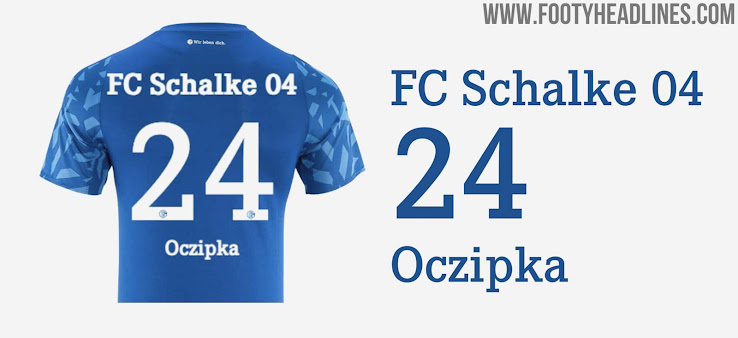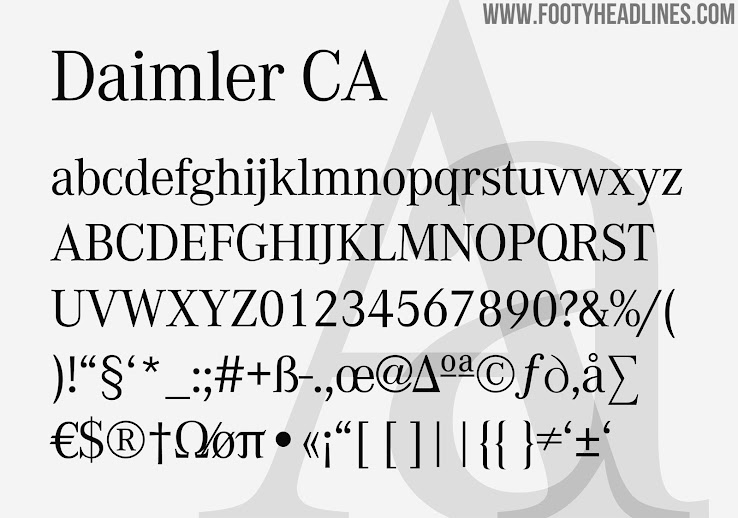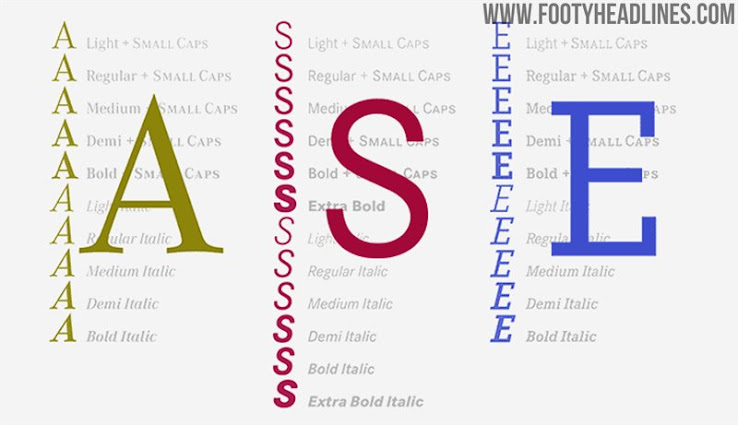
Enthüllt: Schalke 04 Trikot-Schrift ist identisch mit Mercedes-Benz-Schriftart
Vor Beginn der Saison 2018-2019 wechselte der Bundesligist FC Schalke 04 von Adidas zu Umbro. Damals wurde auch eine neue Schriftart für die Trikots vorgestellt. Nun hat uns der Schriftdesigner Christoph Koeberlin von @sportsfonts_com darauf aufmerksam gemacht, dass die Schalke 04 Schriftart nicht einzigartig ist, sondern der Schrift eines berühmten deutschen Unternehmens entspricht.
FC Schalke 04 Trikot-Schriftart
Die S04-Schriftart ist keine für den Klub entworfene Schrift, sondern dieselbe Schriftart wie die des deutschen Automobilherstellers Mercedes-Benz.
Die Mercedes-Benz Schriftart wurde nicht von Daimler-Benz, sondern von Kurt Weidemann entworfen. Sie wird Corporate A-S-E genannt. Corporate A-S-E ist eine dreiteilige Schrift, die Kurt Weidemann zwischen 1985 und 1989 als (zunächst) exklusive Unternehmensschrift für Daimler-Benz entworfen hat.
Weidemann beschrieb die grundlegenden Merkmale der Schrift wie folgt: "Zeitlose Ausgewogenheit, Neutralität, maximale Lesbarkeit, sparsamer Zeichenabstand, Bedruckbarkeit auf verschiedenen Papiersorten in allen wichtigen Verfahren (bis hin zum Sieb-, Flexo- und Laserdruck), Lesequalität auf Bildschirmen, in der Lichtwerbung und in verschiedenen Bildauflösungsverfahren und Einheitsplänen (Raster, Linien, Punkte pro Zoll) der Verlagssysteme.
Die Schrift von Schalke 04 ist interessanterweise klein geschrieben. Das macht es sehr deutlich, dass die Schriften gleich sind, nur mit unterschiedlichen Dicken.
Bevor Schalke 04 auf die aktuelle Schriftart umgestiegen ist, trug man nicht die Mercedes-Schriftart.